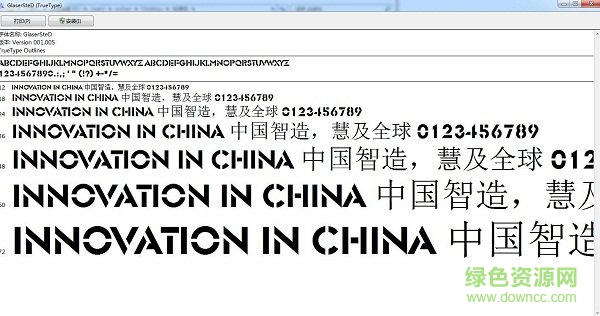
glasersted regular字體是一款非常有辨識(shí)度的英文創(chuàng)意字體,該字體在字母中間嵌入空白間隔,適用于動(dòng)漫、游戲、商業(yè)海報(bào)設(shè)計(jì)等領(lǐng)域,歡迎大家免費(fèi)下載!
字體的發(fā)展和變革已有悠久的歷史,按形態(tài)特征簡(jiǎn)單分為舊字體(手寫(xiě)體)、過(guò)渡字體(印刷體)、現(xiàn)代字體(機(jī)打字體)
任何字體都有其獨(dú)特的風(fēng)格,有的讓人感覺(jué)現(xiàn)代、古典; 柔美、剛毅; 迅速、緩慢; 穩(wěn)重、輕盈…
在設(shè)計(jì)時(shí),通常為表達(dá)某種情感而選擇字體。對(duì)字體情感的產(chǎn)生是因?yàn)閷?duì)某種字體的內(nèi)在韻律,而產(chǎn)生的視覺(jué)反應(yīng)。